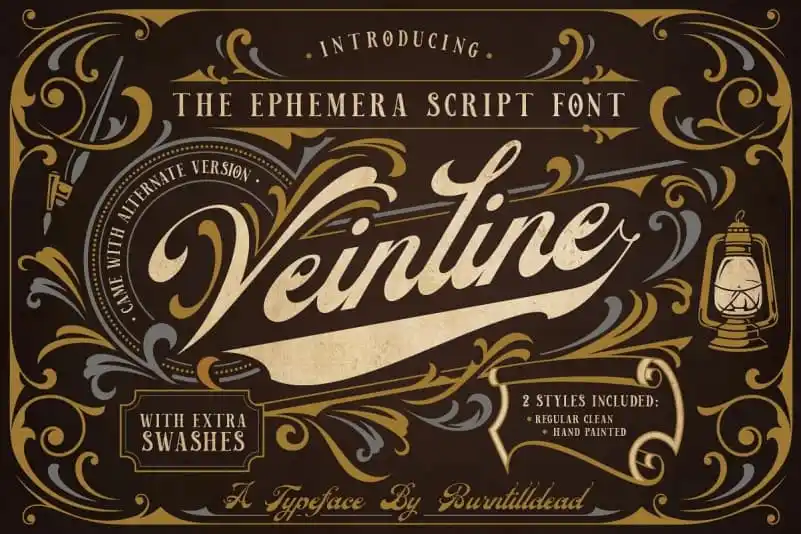
Veinline Script é uma fonte retrô projetada por Burntilldead que combina letras com ornamentos acentuados. Inspirada nas antiguas etiquetas para pratos, cartões de certidão e bilhetes, Veinline Script revela as linhas geométricas e os detalhes arredondados que marcaram o estilo de letras do final do século XIX e início do século XX. Este design retrô oferece uma sensação de nostalgia, remetendo a um tempo em que as empresas criavam sua identidade visual através de designs simples mas impactantes. Com seu formato ornamental, Veinline Script é perfeito para criar mensagens memoráveis que rememoram o passado distante e ao mesmo tempo destacam-se na atualidade, tornando-a uma opção única para designers em busca de um estilo retro que seja inovador e autêntico.